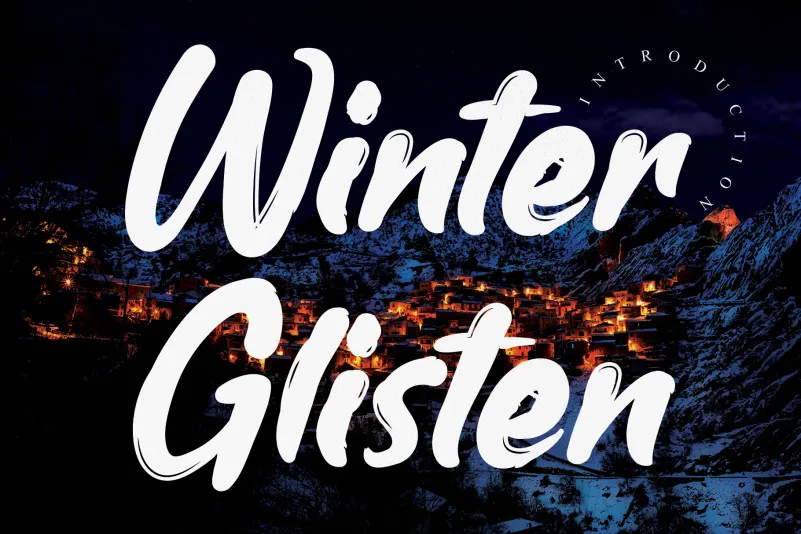
Winter Glisten Script Font – Fonte Grátis
Winter Glisten Script Font
A fonte “Winter Glisten Script” é uma elegante escolha para qualquer projeto de DIY. Seu estilo casual e bold é aperfeiçoado com um toque delicado de ser escrita à mão, usando uma caneta ou pincel. Esta font criativa pode transformar qualquer projeto em algo único e encantador. Ideal para personalizar suas próprias roupas, criar cartões de aniversário especiais ou até mesmo decorar sua casa com um toque artesanal. “Winter Glisten Script” é perfeito para quem procura uma fonte que combinaria bem tanto em ambientes tradicionais quanto em projetos mais modernos, trazendo elegância e originalidade a cada letra escrita. Com seu designer experiente, Andikastudio, garantimos que essa font seja de alta qualidade, com um acabamento perfeito. Acesse agora para descobrir como esta font pode transformar o seu trabalho em algo memorável e único.